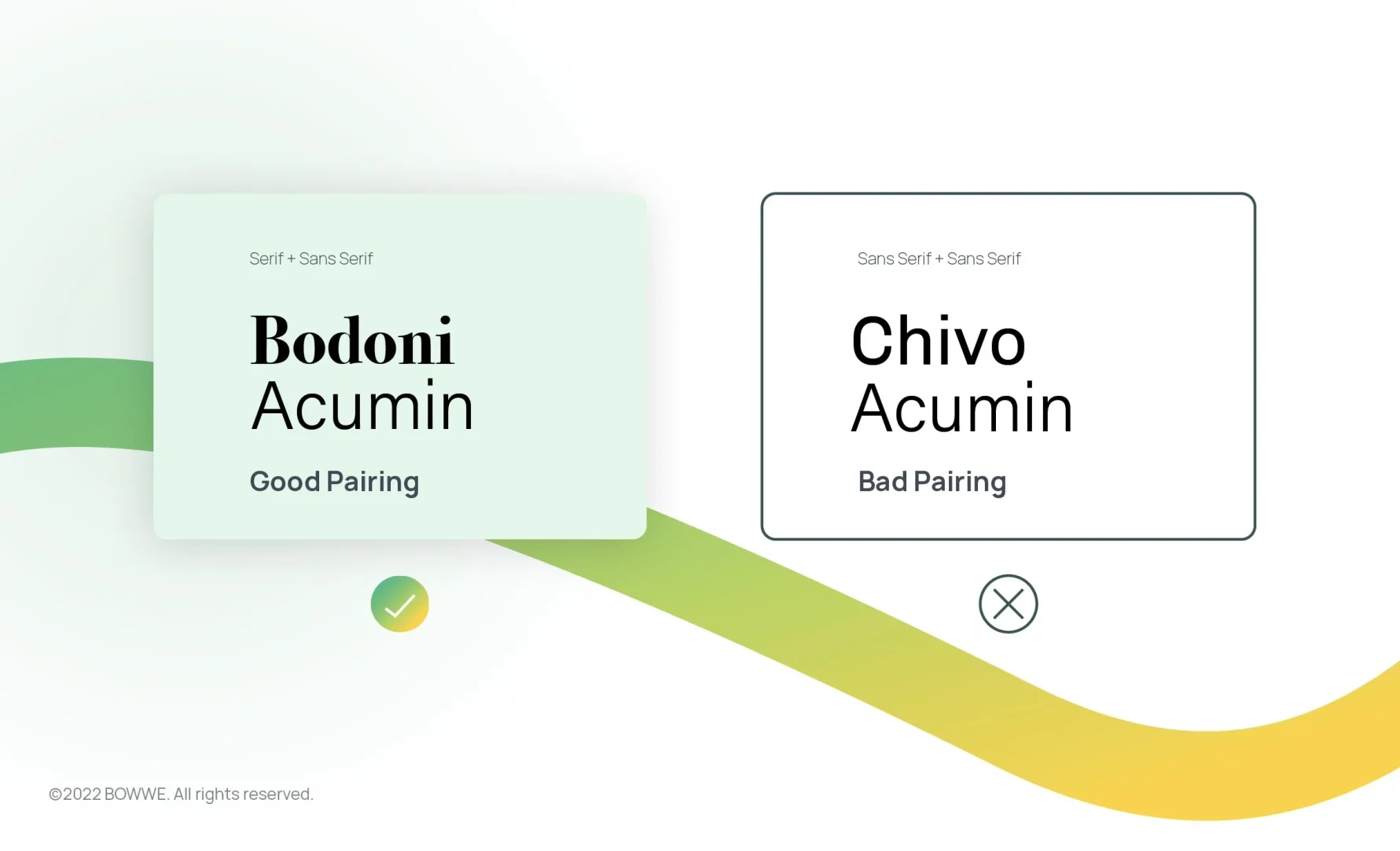
8 règles de typographie d'or pour tirer le meilleur parti de vos polices
Une rue avec des panneaux routiers faisant référence à la typographie
Une typographie bien pensée et bien choisie est essentielle pour obtenir un site Web esthétique et, surtout, facilement lisible. Mais savez-vous comment rendre le texte du site web clair et cohérent avec l'identité de votre marque ?
Ne vous inquiétez pas. J'ai rassemblé les 8 règles de typographie les plus cruciales qui rendront l'ensemble du processus de création de la typographie parfaite pour votre site Web simple et efficace. Assurez-vous de suivre toutes les règles et vous serez récompensé par un système de typographie transparent qui donnera à votre projet un aspect professionnel et améliorera son UX.
8 principes de typographie à suivre
1. Choisissez la bonne police
Le plus important est que votre typographie reflète la vraie nature de votre industrie. Par conséquent, choisir la bonne typographie de site Web ne peut pas être une question de hasard. Ce n'est pas parce qu'une police est populaire et que vous l'aimez qu'elle conviendra à votre marque. Faites attention à ce que la police communique et si elle correspond au style de votre marque.
Graphique - Choisissez la bonne police
Faites attention à ce que la police communique et si elle correspond au style de votre marque. Si vous dirigez un magasin pour enfants, vous n'utiliserez pas de polices professionnelles simples et élégantes et vice versa. Associez toujours les polices à la communication de votre marque pour être cohérent avec celle-ci.
2. Sélectionnez la taille de la police
La taille de la police sur la page est importante ! Si vous choisissez une police ni trop petite ni trop grande, vous faciliterez grandement la lecture de vos utilisateurs. Une unité spéciale utilisée par les typographes pour décrire les polices est "pt" ou "point".
La plage préférée de tailles de police standard pour les sites Web se situe entre 14 et 25 points. Des polices plus grandes peuvent être réservées pour les titres - 20 pt et plus , et pour le texte brut, la meilleure plage est de 14 à 18 pt.
Graphique - Sélectionnez la taille de la police
Quelle que soit la taille de police que vous choisissez, assurez-vous que la taille de police :
a) rend le texte lisible - une taille de police de 12 points et moins peut nuire considérablement à la lisibilité ;
b) correspond à la police de caractères - par exemple, pour sa police système Roboto Google recommande un minimum de 16 pt. D'autre part, San Francisco - la police utilisée, entre autres, dans les appareils Apple, devrait avoir une taille d'au moins 18 points ;
c) reflète l'objectif du site Web - si la page n'est pas dominée par le texte mais par la conception, vous pouvez utiliser une police plus petite. Aussi dans le cas de pages interactives incitant l'utilisateur à cliquer à chaque étape, cette solution peut être envisagée. Si, en revanche, vous avez affaire à un site Web où le texte domine et où la tâche principale de l'utilisateur est la lecture (par exemple, zone de blog, portail d'informations), il est préférable de choisir une police légèrement plus grande.
Comment choisir la taille de l'en-tête ?
Vous avez décidé de la taille de la police de votre corps de texte mais vous ne savez pas comment conserver la taille des titres proportionnellement au reste du contenu ? Il existe plusieurs bonnes pratiques pour cela :
a) L'en-tête H1 doit correspondre à 300 % de la taille de police utilisée dans le corps du texte. Par exemple, si votre site Web utilise une police de 18 points pour votre corps de texte, la taille optimale pour vos en-têtes est de 54 points.
b) L'en-tête H2 doit correspondre à 200 % de la taille de police du corps du texte. Dans ce cas, avec une taille de police de base de 18 pt, le titre H2 idéal serait de 36 pt.
⚡BOWWE Growth Hack:
Pour les rubriques successives, vous pouvez diminuer progressivement le pourcentage ; par exemple, pour l'en-tête H4, vous pouvez multiplier la taille de la police principale par 130-150 %.
Polices dans la version mobile
Graphique - Polices dans la version mobile
Lors du choix de la taille de la police, vous devez répondre à la question sur quels appareils le texte sera affiché. La taille de la police sera différente sur les moniteurs d'ordinateurs portables que sur les appareils mobiles. Si vous préférez vous concentrer sur l'apparence du site Web sur les appareils mobiles, rappelez-vous ces deux règles importantes :
a) Sur les écrans de smartphone, une grande police n'aura pas l'air sympa,
b) Les titres ne doivent pas dépasser deux lignes.
Par conséquent, lors de la conception d'un site Web mobile, il convient de vérifier l'apparence du texte et de s'assurer que la police n'est pas trop grande.